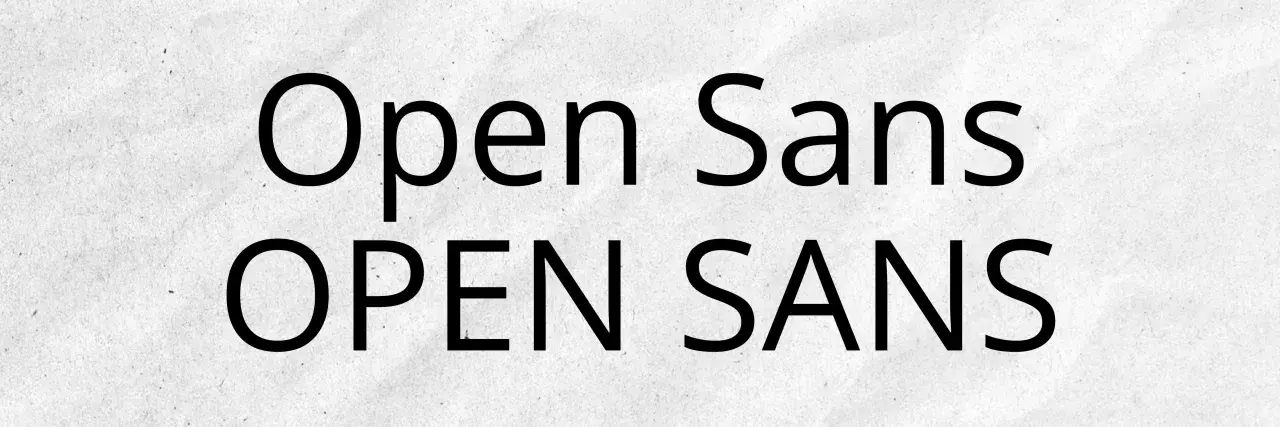
Font cyfrowy - jak wybrać, by strona zyskała?
Dwie linie tekstu: "Open Sans" i "OPEN SANS". To popularna cyfrowa czcionka, znana ze swojej czytelności.
Cyfrowa czcionka to w praktyce krój pisma, który ma wspierać ekran, interfejs albo techniczny charakter projektu, a nie tylko ładnie wyglądać. W tym tekście pokazuję, jakie są najważniejsze typy takich fontów, gdzie sprawdzają się najlepiej i jak dobrać je do strony internetowej lub sklepu, żeby nie zepsuć czytelności, szybkości i odbioru marki. Zwrócę też uwagę na błędy, które najczęściej kosztują najwięcej.
Najważniejsze rzeczy, które warto wiedzieć przed wyborem fontu
• Font o technicznym lub cyfrowym charakterze działa najlepiej tam, gdzie liczy się precyzja, nowoczesność i wyraźna struktura.
• Najbezpieczniejsze są kroje proste: monospace, bezszeryfowe i dobrze zaprojektowane fonty display z ograniczonym użyciem.
• Na stronie internetowej taki krój warto stosować głównie w nagłówkach, liczbach, interfejsach, dashboardach i elementach akcentowych.
• Do długich akapitów lepiej wybierać bardziej neutralne fonty, bo techniczny styl szybko męczy wzrok.
• Przy wdrożeniu liczą się też detale: polskie znaki, rozróżnienie cyfr, liczba odmian, waga plików i czytelność na mobile.
Czym właściwie jest font o cyfrowym charakterze
Ja patrzę na taki krój przede wszystkim jak na narzędzie komunikacji. Ma on sugerować technologię, porządek, nowoczesność albo precyzję, dlatego zwykle opiera się na prostych kształtach, mocnym rytmie liter i wyraźnym podziale znaków. W praktyce ludzie nadal często mówią „czcionka”, ale w świecie stron internetowych i projektów graficznych chodzi zazwyczaj o font, czyli cyfrowy zapis kroju pisma.
To rozróżnienie nie jest akademickim detalem. Jeśli projekt ma być czytelny na ekranie, font musi dobrze zachowywać się w różnych rozmiarach, obsługiwać polskie znaki i nie tracić formy przy małej rozdzielczości. Właśnie dlatego w projektach technicznych tak dobrze sprawdzają się kroje z prostą konstrukcją, wyraźnymi odstępami i spokojnym światłocieniem liter.
W mojej ocenie najważniejsze jest to, czy font wspiera treść, czy tylko odgrywa rolę ozdobną. Gdy krój ma mówić o technologii, ale nadal ma ułatwiać odbiór informacji, projekt zwykle zyskuje. Gdy jest zbyt efektowny, zaczyna przeszkadzać już po kilku sekundach. I właśnie od tego rozróżnienia warto przejść do konkretnych typów.
Typografia w Web Designie. Duże litery
Jakie typy fontów cyfrowych spotyka się najczęściej
W praktyce nie ma jednego uniwersalnego stylu. Inny efekt daje krój przypominający terminal, inny font inspirowany tablicami LED, a jeszcze inny geometryczny sans-serif używany w aplikacjach i interfejsach. Poniżej zebrałem najczęstsze kierunki, bo właśnie one najczęściej pojawiają się w projektach internetowych, brandingowych i produktowych.
Typ Charakter Gdzie działa najlepiej Na co uważać
Monospace Każdy znak zajmuje podobną szerokość, co daje wrażenie porządku i technicznej precyzji. Kod, terminale, dokumentacja, panele administracyjne, etykiety z danymi. W długich tekstach bywa chłodny i męczący, więc lepiej używać go punktowo.
Sans-serif techniczny Prosty, czysty, nowoczesny, zwykle bez ozdobników i z dobrą czytelnością. Strony firm technologicznych, SaaS, e-commerce, UI, nagłówki i sekcje informacyjne. Zbyt neutralny font może stać się anonimowy, jeśli nie ma charakteru marki.
Pixel / bitmap Styl kojarzący się z grami, retro elektroniką i estetyką dawnych ekranów. Projekty gamingowe, landing page’e, brandy retro-futurystyczne, grafiki promocyjne. Na małych ekranach i w treści użytkowej szybko traci czytelność.
OCR / cyfrowy display Litery i cyfry przypominają znaki rozpoznawane maszynowo albo segmentowe wyświetlacze. Panele pomiarowe, aplikacje techniczne, wizualizacje danych, branding przemysłowy. Łatwo przesadzić z efektem „gadżetu” i zrobić z projektu dekorację bez funkcji.
Stencil / industrial Litery mają wycięcia i kojarzą się z przemysłem, logistyką, sprzętem i infrastrukturą. Marki techniczne, automotive, przemysł, logistyka, identyfikacja produktów. W body copy zwykle odpada, bo bardziej buduje klimat niż komfort czytania.
Futuristic / display Wyraźnie stylizowany, często geometryczny i mocno charakterystyczny. Nagłówki, logotypy, kampanie, hero sekcje, okładki i bannery. Dobrze wygląda krótko, ale w dłuższym użyciu szybko dominuje treść.
Gdybym miał wskazać najpraktyczniejszy wybór dla stron internetowych, postawiłbym na proste sans-serify i monospace. To one najłatwiej łączą wygląd techniczny z realną użytecznością. Bardziej efektowne kroje zostawiłbym do nagłówków, etykiet i krótkich komunikatów, bo tam mogą naprawdę pracować na charakter marki.
Najczęstszy błąd? Traktowanie stylu tech jak jednego worka. Tymczasem font do dashboardu, font do gamingowego landing page’a i font do opakowania produktu to trzy różne zadania. Ta różnica będzie miała znaczenie również wtedy, gdy przejdziemy do konkretnych miejsc na stronie, gdzie taki krój daje najlepszy efekt.